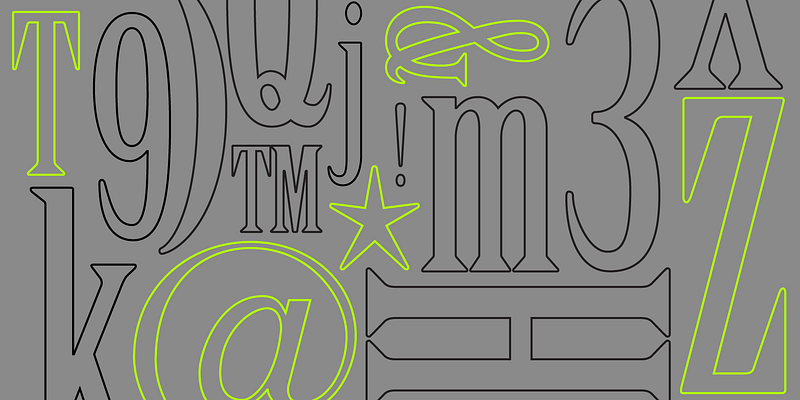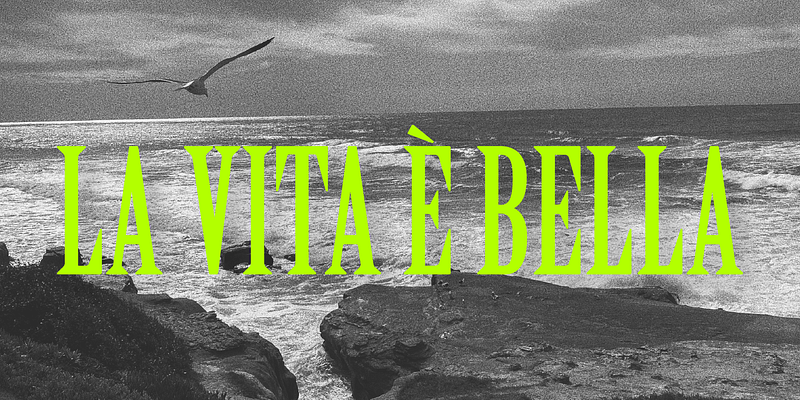
Birch es un tipo de letra de Adobe Originals diseñado en 1990 por Kim Buker Chansler. Birch se basa en un tipo de madera Latin Condensed que se encuentra en un libro de muestras de William Page de 1879; Birch es un tipo de letra condensado para cartelería especialmente legible que destaca por sus serifas angulares. debe usarse con moderación en trabajos de cartelería.
El programa Adobe Originals se inició en 1989 como tipográfica interna de Adobe, creado para desarrollar tipos de letra originales con una calidad de diseño ejemplar, fidelidad técnica y longevidad estética.
En la actualidad, la misión del equipo de Type es crear tipos de letra sofisticados e incluso experimentales que exploren las posibilidades del diseño y la tecnología. Los tipos de letra que se publican como originales de Adobe son el resultado de años de trabajo y estudio, y se consideran estándares del sector por la ambición y la calidad de su desarrollo.